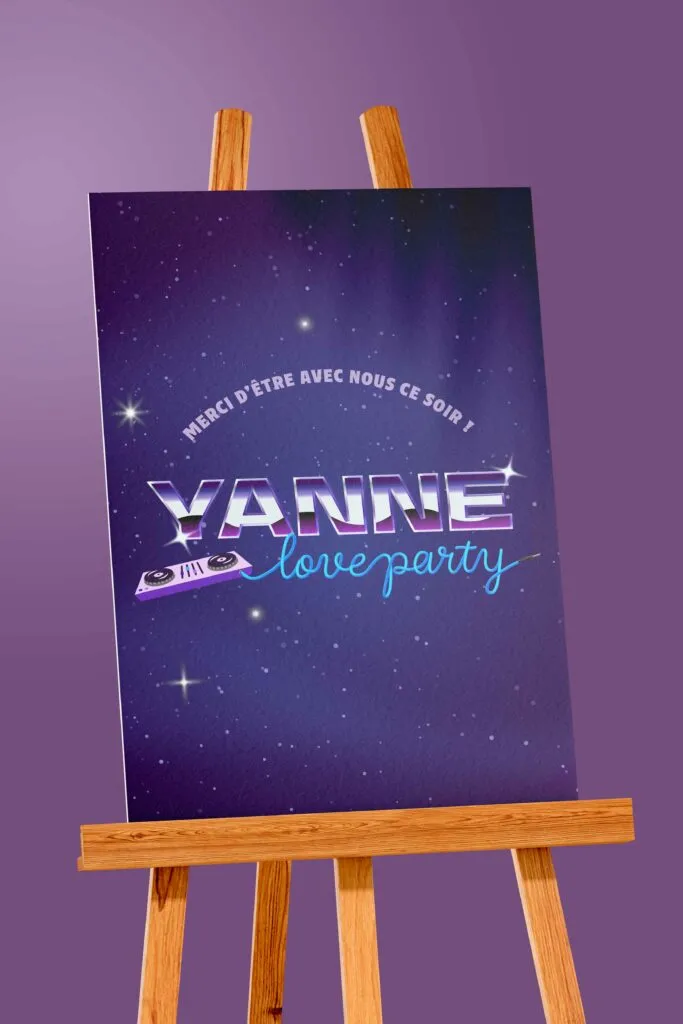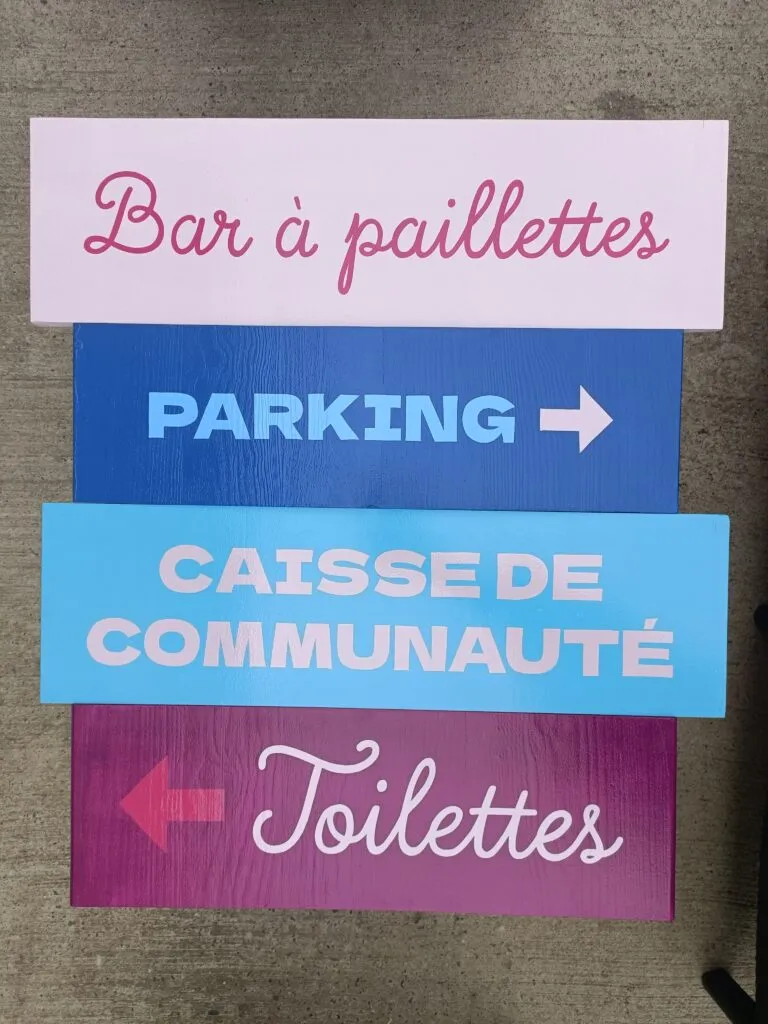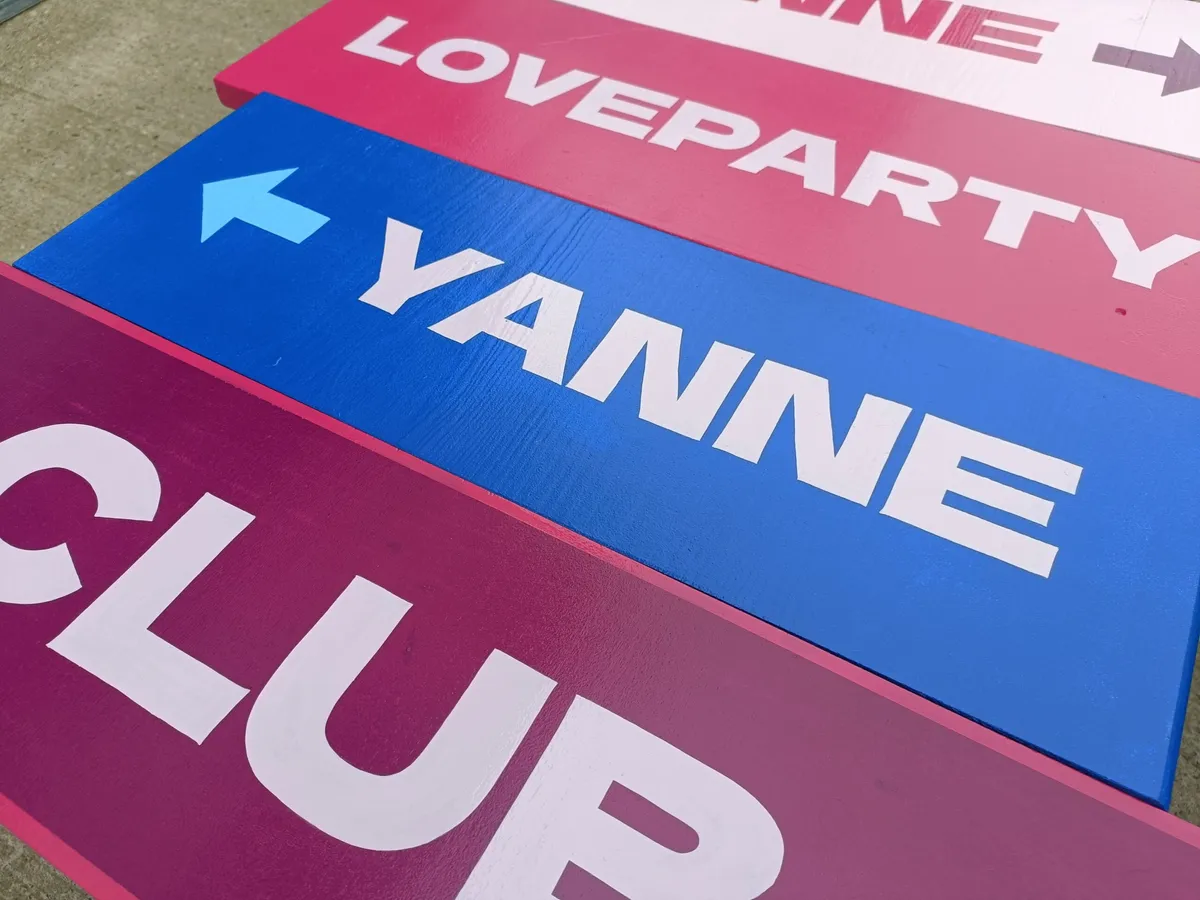
Love Party Mariage
Identité visuelle et signalétique mariage
Création d’une identité visuelle pour une fête/festival de mariage, création des faire-parts, de bracelets de festival et de toute la signalétique peintes à la main sur des planches de bois de récup
Thème : Retro années 80/90 focus DJ et système son